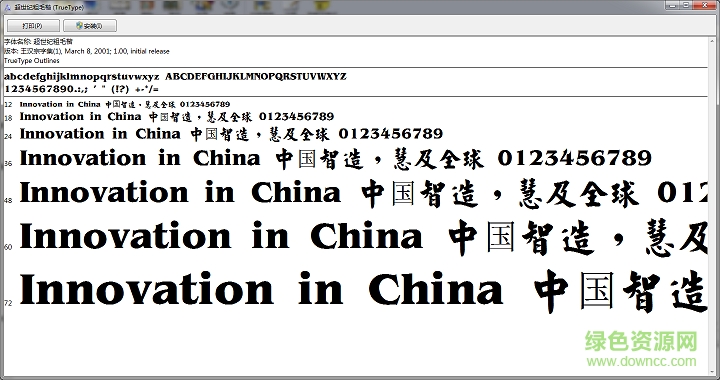
超世紀(jì)粗毛楷字體是一款筆畫很粗的簡(jiǎn)體字體,但是,用超世紀(jì)粗毛楷書寫的漢字,其中會(huì)有一個(gè)是細(xì)體字,非常顯眼,也適合朋友們?cè)谥谱魈厥馕恼滦畔⒌臅r(shí)候使用,非常的實(shí)用,需要的朋友就請(qǐng)登陸綠色資源網(wǎng)下載使用吧!